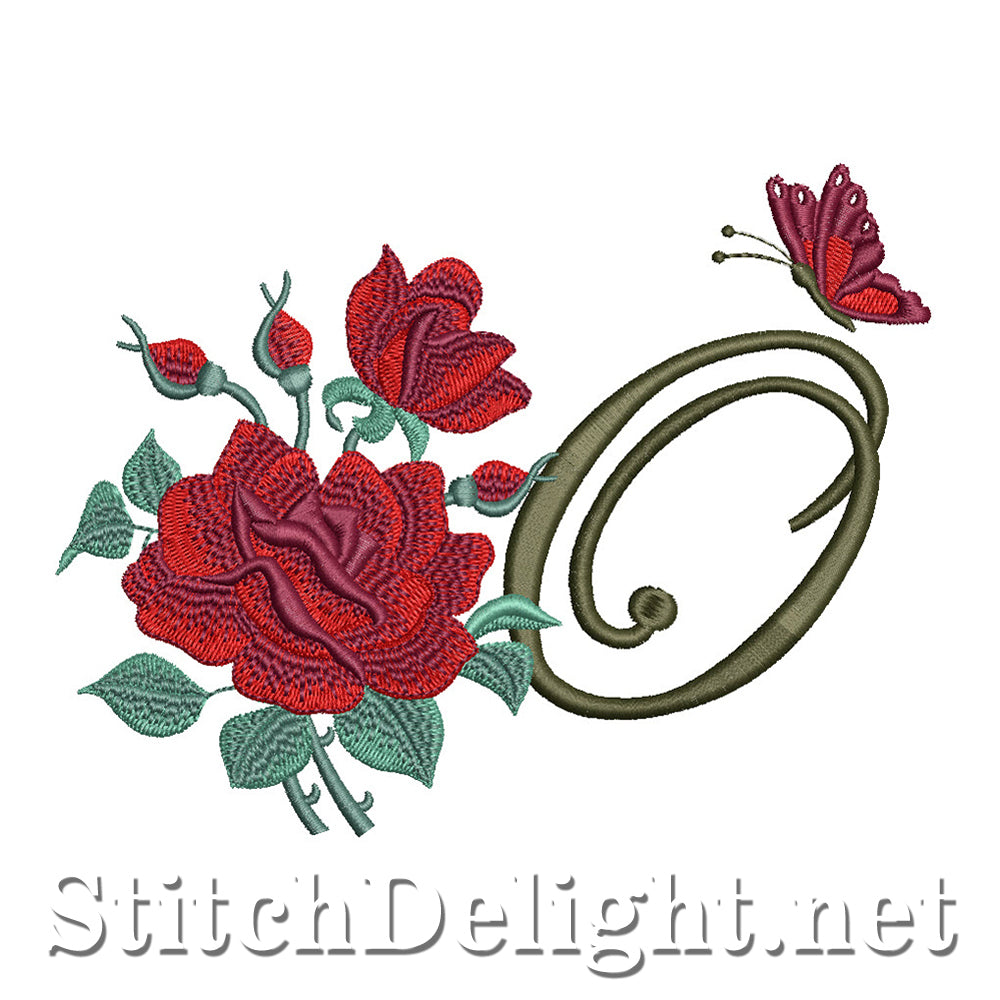
SDS1654 Belle Rose Police O
Ça ne devient pas plus romantique que ça. La lettre simple Beautiful Rose est faite avec amour pour le cerceau 5x7. Faites vos propres cadeaux spéciaux en cousant son nom sur une couverture/taie d'oreiller.